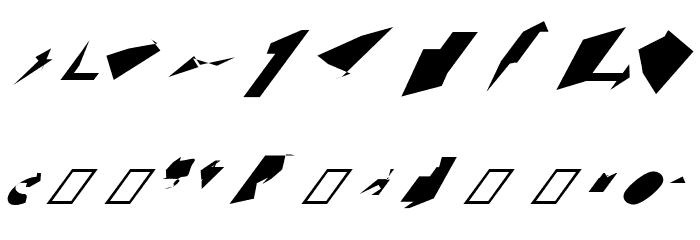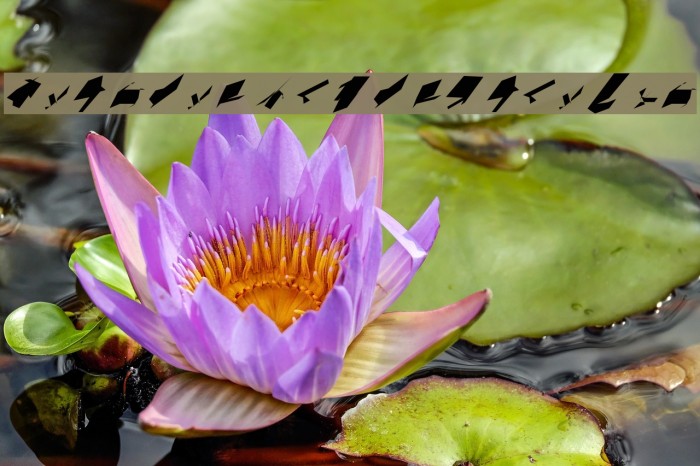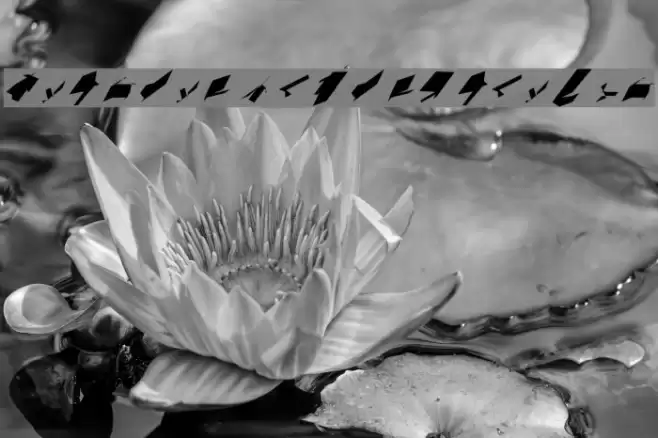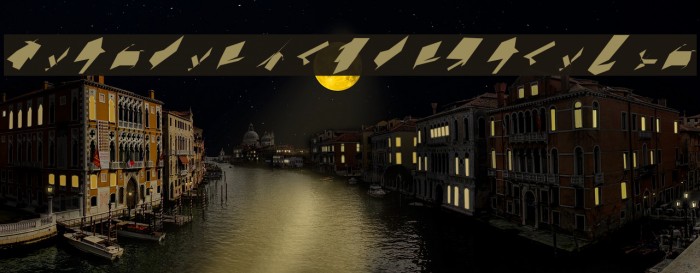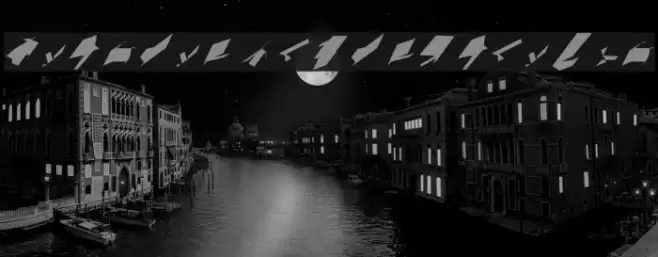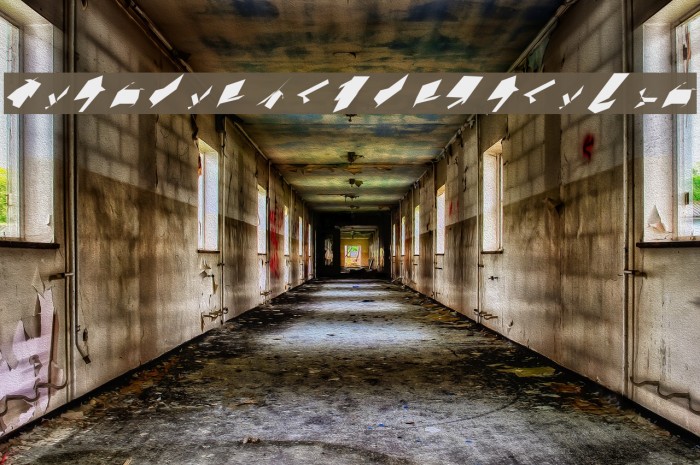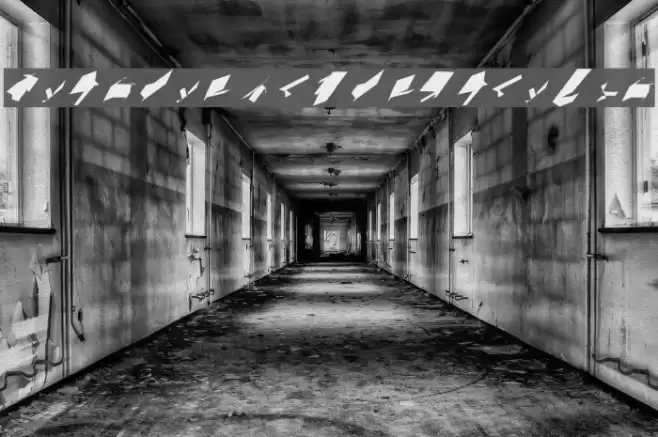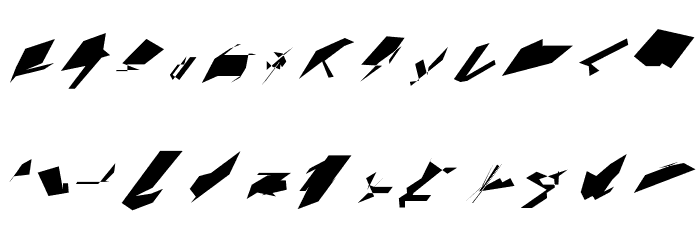
Siberia UltraOblique Font
| Caz de utilizare | Logos, Artistic designs, Posters |
| Proiecte propuse | Ideal for avant-garde art projects, experimental design work, or as a striking element in modern posters and album covers. |